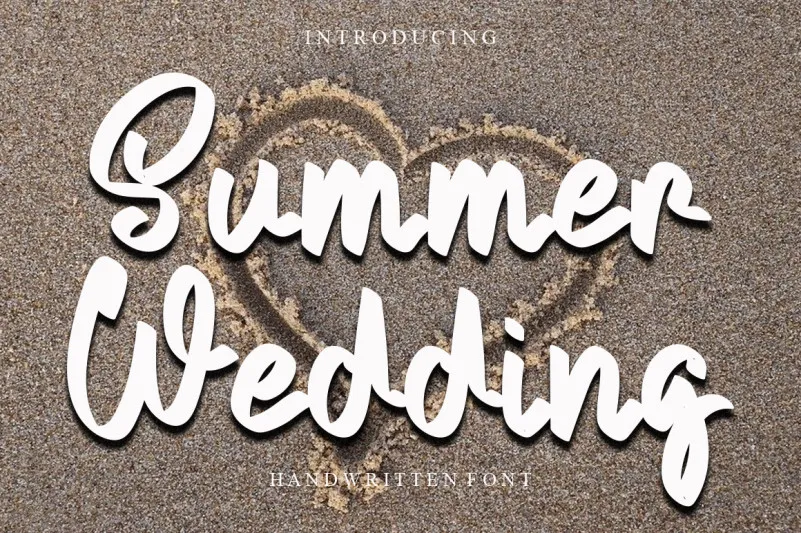
Summer Wedding Font – Download Grátis
Este é um fonte script único, divertido e simpático, perfeito para quem busca algo que combine elegância com uma pitada descontraída. Seja você buscando um texto de rede social ou uma caligrafia para projetos DIY, este fonte transformará qualquer ideia criativa em verdadeiros artefatos únicos e inspiradores. A LevinCreative trouxe a nossa página uma nova opção de fontes de alta qualidade que adiciona aquela pitada extra especial ao seu trabalho artístico. Escolha Summer Wedding Font para dar um toque único e pessoal aos seus projetos.